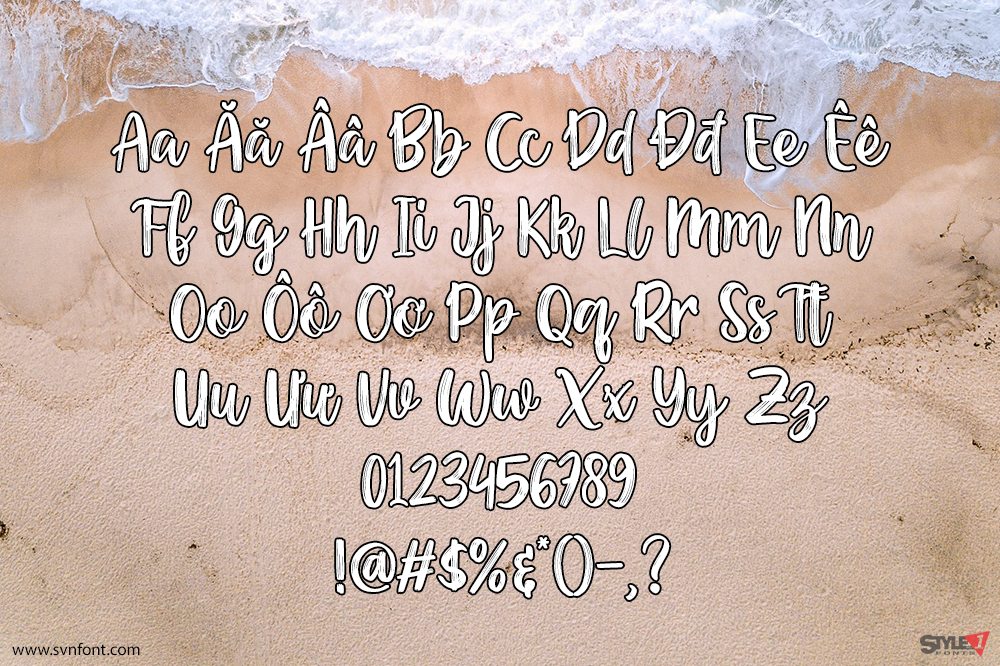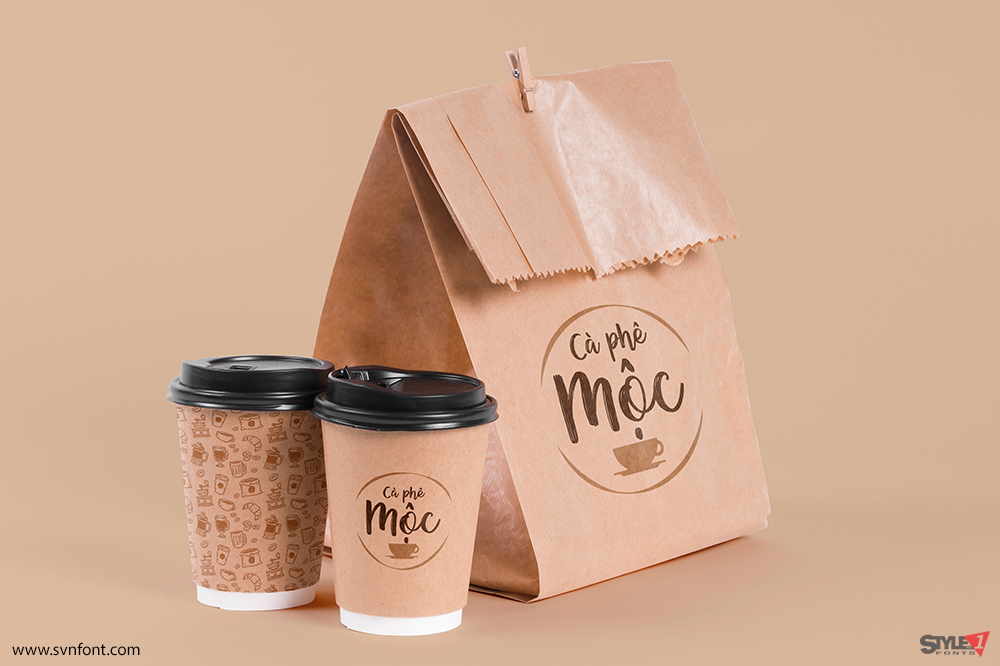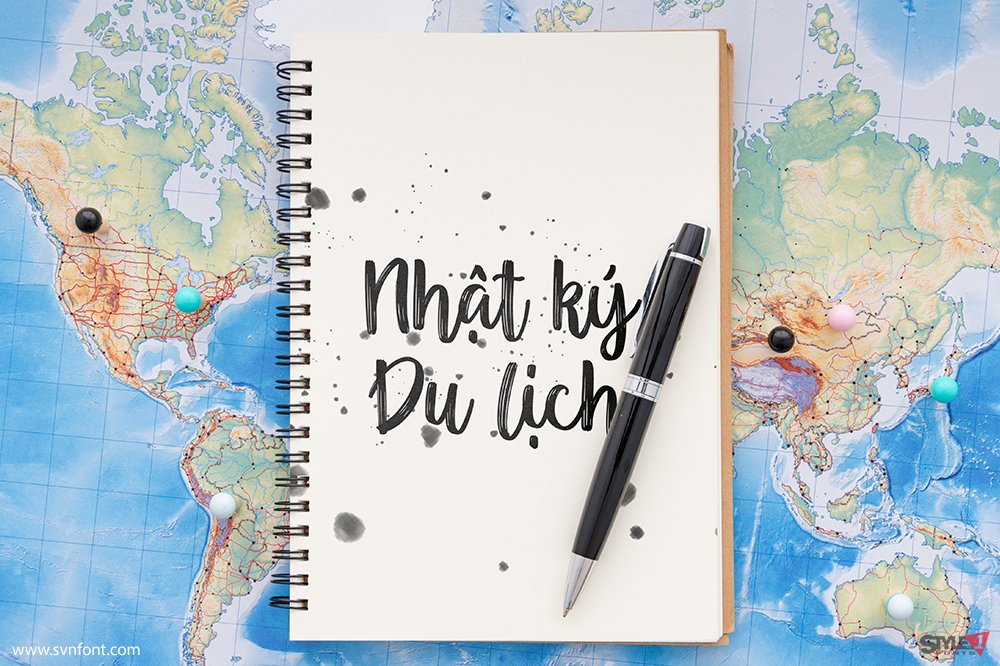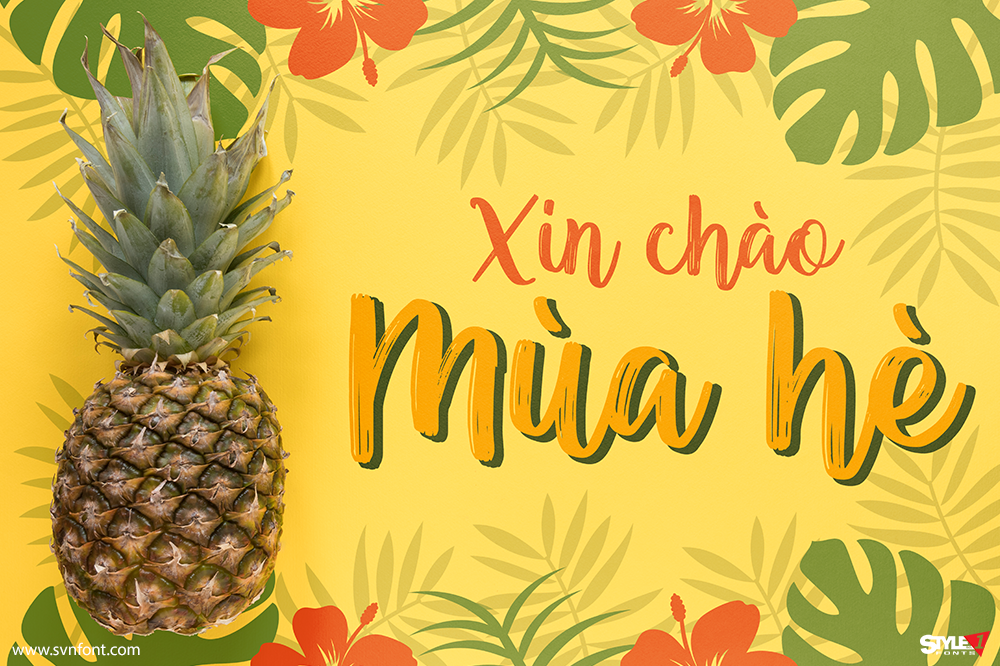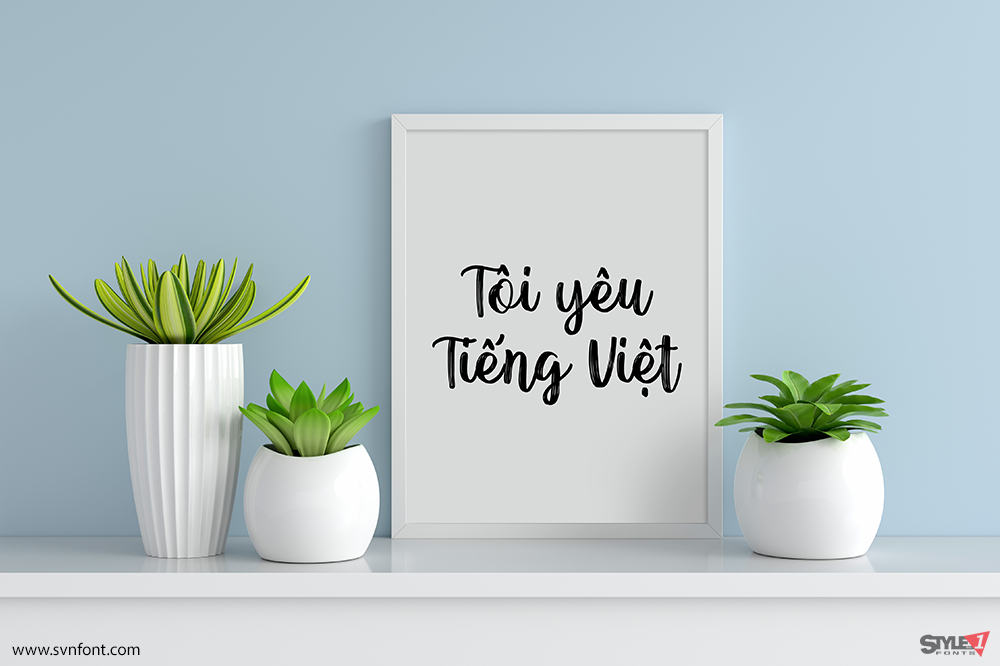
Paradise – một brush font cực kỳ đáng yêu dành cho các thiết kế tiếp theo của bạn, font giữ được độ khô – ướt đặc trưng của kiểu font cọ vẽ. Font thích thợp cho thiết kế banner quảng cáo, bao bì sản phẩm, thực đơn ăn uống,…